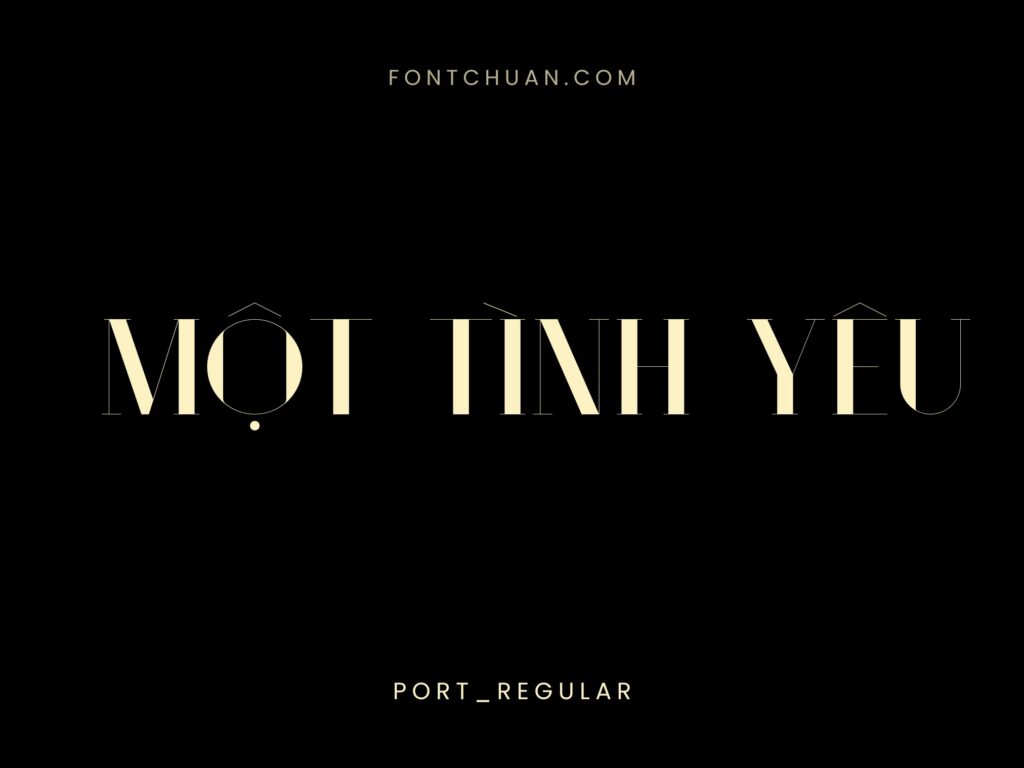
Font iCiel Port Việt Hóa
Port là một kiểu chữ Didone thử nghiệm với phong cách hiện đại, được thiết kế bởi João Oliveira và phát hành bởi Onrepeat vào năm 2013. Font này lấy cảm hứng từ các tác phẩm kinh điển của Bodoni và Didot, kết hợp với sự tinh tế của các kiểu chữ viết tay, tạo nên sự độc đáo và sáng tạo trong thiết kế. Đặc biệt, Port đã được Việt hóa bởi iCiel, hỗ trợ tiếng Việt cùng nhiều ngôn ngữ khác, đáp ứng nhu cầu đa dạng của người dùng. Thành viên của Font Chuẩn đã sưu tầm và chia sẻ font này, giúp cộng đồng thiết kế ứng dụng dễ dàng trong các dự án của mình.
Về đặc điểm thiết kế, Port sở hữu các ký tự với đường nét thẳng và tương phản mạnh, kết hợp với các nét uốn lượn tinh tế, tạo nên sự cân đối giữa cổ điển và hiện đại. Font này phù hợp cho các thiết kế như logo, tiêu đề, poster, bao bì sản phẩm và các ấn phẩm truyền thông cần sự sang trọng và nghệ thuật. Ngoài ra, Port còn thích hợp cho các ngành nghề như quảng cáo, thời trang, thiệp cưới và spa, cùng các sự kiện đặc biệt như lễ hội, sinh nhật, Valentine và Trung thu.